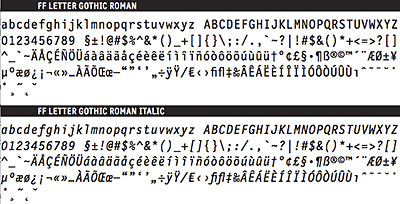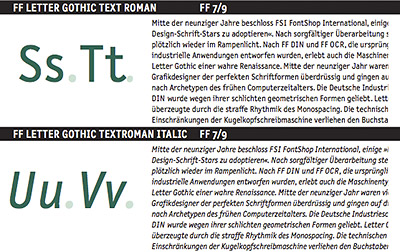
Letter Gothic: KopfarbeiterSie war die erste serifenlose Schreibmaschinentype. Roger Roberson entwarf
Letter Gothic 1956 für die elektrischen IBM-Modelle. In den 1990er Jahren
kam die digitalisierte Version der Schrift wieder in Mode. FSI FontShop
![]() Die größte Schwäche der Schreibmaschine war schon immer
ihre einheitliche Buchstabenbreite. Die Zeichen W und i litten am
meisten darunter: ersteres wurde auf engem Raum zusammengepresst, das i bekam
einen breiten Fuß und am Kopf eine Halbserife – dies alles ist bei
der Schrift Courier sehr gut zu besichtigen.
Lange Zeit waren Serifenschriften das bevorzugte Modell für das Entwerfen von Schreibmaschinentypen. Die Endstriche dienten den Designer als Spielball, um schmale Buchstaben breit zu machen und breite Lettern zu verschmälern. Im Herbst 1958 wagte sich der IBM-Ingenieur Roger Roberson an ein Experiment, dem seine Kollegen keine großen Chancen einräumten. Tag und Nacht zeichnete Roberson an einem Alphabet für IBM-Schreibmaschinen mit gleichen Buchstabenbreiten, die allesamt ohne Füßchen auf ihrer gedachten Schriftlinie standen. Dies waren die Geburtswochen der Schrift Letter Gothic. ![]() Ganzseitige Anzeige für die Kugelkopfschreibmaschiene IBM Selectric aus dem Jahre 1962 (Scan: Fontblog) Die IBM Selectric machte Letter Gothic weltberühmt. Das Modell überzeugte mit einem gänzlich neuen Konstruktionsprinzip: statt Typenhebel brachte eine drehende Kugel die Buchstaben zu Papier. Die Kugelkopfschreibmaschine war ein mechanisches Meisterwerk und äußerst komplex konstruiert. IBM hielt über mehrere Jahre ein Patent für diese Technologie und eroberte damit fast im Alleingang die Büros. Durch den austauschbaren Kugelkopf (engl: golf ball) konnten die Benutzer erstmals mit unterschiedlichen Schriftgrößen und Schriftarten schreiben. Letter Gothic ist eine »mono-spaced« Schrift, auch »fixed-pitch« oder »nicht proportional« genannt. Dies bedeutet, dass der Raum (genauer: die Summe aus Vor-, Zeichen- und Nachbreite) für alle Buchstaben gleich groß ist. Pitch als Maßeinheit bezeichnet die Anzahl der Buchstaben pro Zoll (auf der Waagerechten). Ein Kugelkopf mit der Kennzeichnung 12 (Pitch) enthielt also eine Schrift, die geschrieben 12 Zeichen pro Zoll ergab. ![]() IBM-Kugelkopf (golf ball) mit Letter Gothic 12 Pitch und 96 Zeichen (Foto: Fontblog) Die Höhe der Buchstaben wird in Punkt gemessen. Beim Schreiben am Computer lassen sich sowohl die Punktgröße als auch der/die/das Pitch verändern. Dabei verhalten sich Punkt und Pitch umgekehrt proportional. Wenn eine 12 Punkt große Schrift 10 Pitch entspricht, dann wird sie 5 Pitch bei 24 Punkt und 20 Pitch bei 6 Punkt. Als Ende der 1980er Jahre das Desktop Publishing (DTP) geboren wurde, war die Schreibmaschine in der Bürokommunikation bereits auf dem Rückzug. Briefe und Faxe wurden mit einer Textverarbeitung am PC verfasst und auf einem Nadeldrucker ausgegeben. Dann kamen Laserdrucker und die Auswahl der Schriften wuchs ins Unermessliche. Gleichwohl überlebten einige Schreibmaschinen-Klassiker, denn auch im Computerzeitalter sollten maschinen-geschriebene Briefe wie Briefe aussehen und nicht wie eine Zeitungsspalte, gesetzt in Times. Die Courier gehörte von Anfang an zur Ausstattung der Laserdrucker. Im Sommer 1989 kam auch die populäre Letter Gothic im PostScript-Format heraus. Letter Gothic: alle Zeichen nehmen den gleichen Raum ein FF Letter Gothic Text: proportionale, platzsparende Alternative Zu Beginn der neunziger Jahr waren viele Grafikdesigner der perfekten Schriftformen überdrüssig und gingen auf die Suche nach Archetypen des frühen Computerzeitalters. Die Deutsche Industrieschrift DIN wurde wegen ihrer schlichten geometrischen Formen geliebt. Letter Gothic von Bitstream oder Adobe überzeugten durch die straffe Rhythmik des Monospacing. Jede Menge Schriftentwerfer gingen auf die Bedürfnisse der Anwender ein und kultivierten »behinderte Typen« wie FF Trixie, FF Confidential, FF Dynamoe, FF Blur und FF Magda. Die Deformation der Buchstabenformen als Konsequenz unfähiger Mechanik wurde mit digitaler Technik nachgeahmt und verstärkt. ![]() Eine moderne Schrift bietet über 200 Zeichen ... FF Letter Gothic bietet mehr: neben der PostScript-Standardbelegung befinden sich in einem ergänzenden Expert-Font (für alle Schnitte) mathematische Zeichen, Ligaturen und Symbole Um 1995 beschloss FSI FontShop International, einige »Non-Design-Schrift-Stars zu adoptieren«. Nach sorgfältiger Überarbeitung standen sie plötzlich wieder im Rampenlicht, als FF DIN und als FF OCR F (beide überarbeitet von Albert-Jan Pool). 1996 folgte FF Letter Gothic Text. Die Ausstattung des Originals aus den 60er bzw. 80er Jahren entsprach nicht den Erwartungen an eine moderne Schrift: es gab nur zwei Strichstärken und es fehlten Akzente und Sonderzeichen. FSI beauftragte den italienischen Schriftentwerfer Albert Pinggera, die Letter Gothic soweit anzupassen und zu überarbeiten, dass sie den Anforderungen des Desktop Publishing genüge. ![]() Für den hochwertigen Textsatz gemacht: FF Letter Gothic Text ist nicht mono-spaced, so dass sich im Mengensatz ein wunderbar gleichmäßiges Grau ergibt Die Wiedergeburt des Klassikers Letter Gothic blieb von »Aufhübschungen« verschont, das Schriftbild behielt seine Ungeschliffenheit. Ziel der Neuinterpretation war, die Anwendungsmöglichkeiten der Familie zu vergrößern. Wie der Name »FF Letter Gothic Text« vermuten lässt, weist Pinggeras erste Überarbeitung keine einheitliche Buchstabenbreite auf. Viele Gestalter wollten nämlich Letter Gothic für längere Lesetexte einsetzen, und dafür ist die angenehme Lesbarkeit einer Proportionalschrift Voraussetzung. Daher entschloss sich Pinggera für variable Zeichenbreiten und Buchstabenabstände. Außerdem fügte er eine Menge mathematischer Zeichen hinzu, zum Beispiel Brüche, griechische Buchstaben, Rechenzeichen und Symbole, die man in gesonderten Expert-Zeichensätzen findet. Mediävalziffern mit Ober- und Unterlängen sind Standard bei FF Letter Gothic Text. ![]() Zwei verschiedene Zahlenarten in FF Letter Gothic: Mediäval- (Text) und Tabellenziffern (Mono) Im Jahre 1996 kam die Familie in den Strichstärken Light, Roman und Bold auf den Markt; zwei Jahre später folgten in gesonderten Paketen die Italic-Schnitte, sowie eine komplette Monospaced-Version namens FF Letter Gothic. Dies war ein Entgegenkommen an die frühen Benutzer der FF Letter Gothic Text, die sich zwar über eine ausgebaute Schriftfamilie freuten, aber den authentischen Monospace-Charakter vermissten. Die Text-Version behält ihre Berechtigung als angenehm lesbare Mengensatz-Schrift. Beide Familien eignen sich hervorragend für den gemeinsamen Einsatz, weil alle Zeichen aufeinander abgestimmt sind. Die Tabellenzahlen in FF Letter Gothic sind einer perfekte Alternative zu den Old-Style-Ziffern der FF Letter Gothic Text. Pinggera hat übrigens zu allen drei Strichstärken echte Kursive entworfen, so dass sich insgesamt eine Großfamilie mit 12 Mitgliedern ergab. ![]() Letter Gothic im Lauf der Zeit und in verschiedenen Ausbaustufen: A. Kugelkopf (wenig Kontrast zwischen Roman und Bold) B. Bitstream, 12 Pitch (mit echter Italic) (näher anschauen und Probe setzen) C. Adobe/Agfa (näher anschauen und Probe setzen) D. Monotype (näher anschauen und Probe setzen) E. FontFont Letter Gothic (3 Strichstärken) (näher anschauen und Probe setzen) und Italic (näher anschauen und Probe setzen) Im Jahr 1999 erschien in der FontFont-Bibliothek eine kuriose Sonderform der Letter Gothic namens FF Letter Gothic Slang. Die US-Designerin Susanna Dulkinys hatte sie für den Titel des Wired-Buchs »Jargon Watch: A Pocket Dictionary for the Jitterati« entworfen, das sich dem Vokabular der New Economy und der Nerds widmete. Was liegt da näher, als eine Dialekt-Schrift zu entwickeln. Dulkinys nahm FF Letter Gothic als Ausgangsbasis und leitete eine kompatible Slang-Version ab. ![]() Hardcover des Wörterbuchs Jargon Watch, gesetzt in FF Letter Gothic Slang (Cover- und Type-Design: Susanna Dulkinys; Foto: Fontblog) Der Schöpfer von FF Letter Gothic, Albert Pinggera, über sein Werk: »Ich glaube, dass vielen Gestalter geholfen ist mit den beiden Versionen der FF-Letter-Gothic-Familie: Sie haben die Wahl zwischen Monospace- und Text-Version mit echten Kursiven, die konsequent aufeinander abgestimmt sind. Die alte Letter Gothic war mit ihren zwei Strichstärken und einer schräg gestellten Version mehr als bescheiden ausgebaut. Zudem war der Unterschied zwischen Roman und Bold zu gering. Moderne Reprotechniken verlangen da eine feinere Differenzierung. Insgesamt denke ich, dass FF Letter Gothic für ungezählte Aufgaben eingesetzt werden kann. Natürlich liegt ihr Stärke im Korrespondenz-Bereich, sowie bei Broschüren und Zeitschriften. Aber auch beim Corporate Design und auf Leitsystemen funktioniert FF Letter Gothic hervorragend. Die Möglichkeit, zwischen Monospace und Text wählen zu können, macht die Schrift universell einsetzbar in Überschriften und im Textsatz. Charakteristische Merkmale der Textversion sind die enge Laufweite und das sorgfältige Kerning für mitteleuropäische Sprachen. Darüber hinaus sind die Auswahl an Strichstärken, die Mono-/Text-Alternative und die Verfügbarkeit von Mediävalziffern die wahren Qualitäten dieser Letter-Gothic-Familie. Vom Charakter her würde ich FF Letter Gothic Text als typisches Kind der Neunziger Jahre betrachten, das in einer Reihe steht mit FF Meta, ITC Officina und FF Info. Die monospaced Version hat ihren typischen Schreibmaschinencharakter behalten. Mittlerweile gibt es jede Menge neuer monospaced Schriften am Markt. Letter Gothic ist jedoch vom Ursprung her eine monospaced angelegte Schrift, während viele der heutigen auf Mono getrimmte Text-Versionen sind.« ![]() Albert Pinggera (*1971) lebt und arbeitet in Südtirol (Italien). Von 1990 bis 1992 war er Produktionsassistent bei einer Zeitung in Bozen. Danach wechselte er zum Designbüro Gert Wiescher nach München und später zu MetaDesign nach Berlin, wo er ab 1994 seine typografischen Fähigkeiten vertiefte. Im Herbst 1995 begann er ein Grafik- und Typografie-Studium an der Königlichen Akademie der Künste in den Haag, das er 1997 abschloss. Pinggera führt heute sein eigenes Designbüro in Italien, wo er sich mit der Gestaltung von Büchern, Formularen, Corporate Designs und Leitsystemen beschäftigt. Seit einigen Jahren unterrichtet er Typografie und Schriftdesign an der Akademy für Design in Bozen. Hinweis: FF Letter Gothic ist die Korrespondenzschrift von FontShop. Herausgegeben: Fr - September 2, 2005 at 01:18 nachm. | |